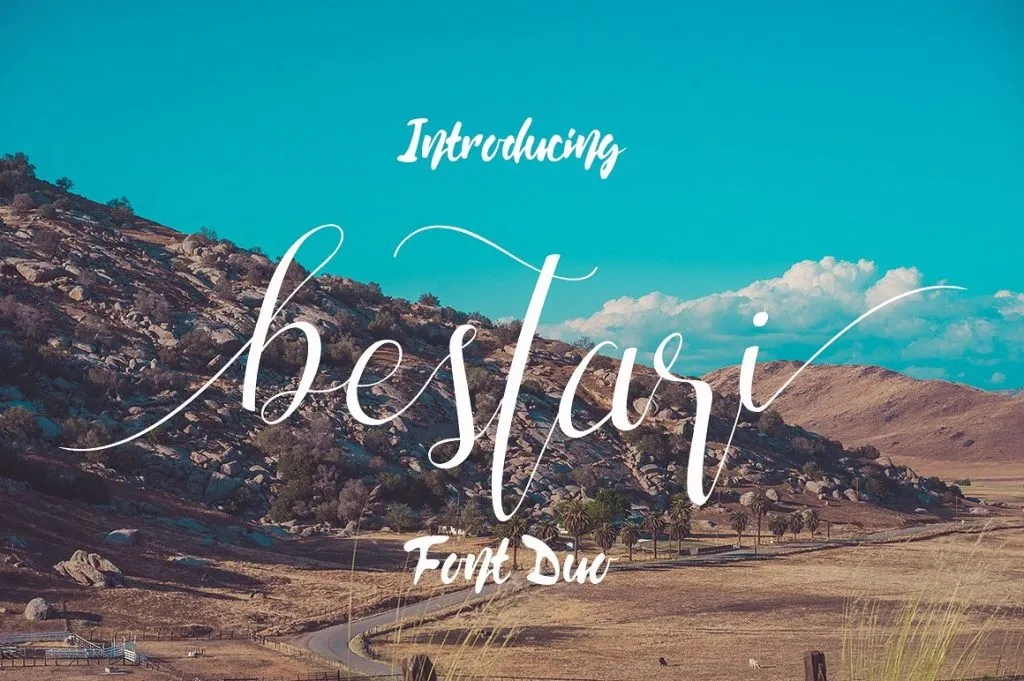
Bestari Script Font – Download Grátis
A fonte ‘Bestari Script’ é uma fusão suave entre a letra cursiva moderna e os traços artesanais de uma ferramenta de desenho. Cada caractere foi cuidadosamente moldado para que sua escrita ganhe um brilho especial, proporcionando um visual elegante e sofisticado. Esta fonte é perfeitamente adaptável a uma ampla gama de usos, desde cabeçalhos chamativos até cartões de casamento ou selos, passando por cartas de corretagem e até mesmo para criar identidades visuais de marcas. Sua simplicidade e modernidade tornam-a ideal tanto para aqueles que procuram uma fórmula clássica quanto para aqueles que desejam um estilo único e contemporâneo. Com a fonte ‘Bestari Script’, você pode transformar qualquer texto em arte impecável, adequando-a à sua necessidade específica de design.